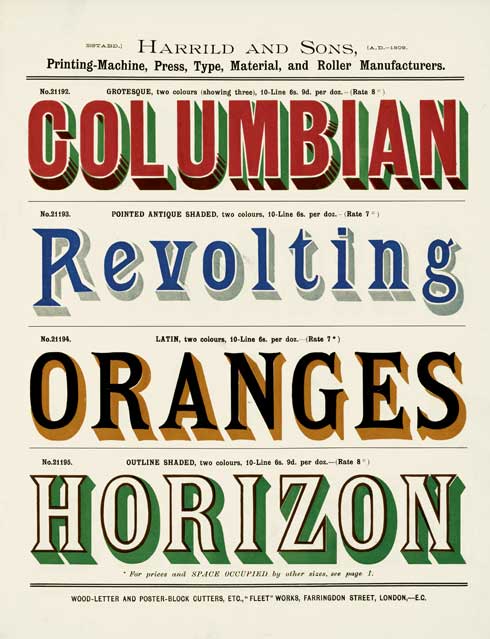
Ich staunte nicht schlecht, als ich eben von unserem Einkauf dieses Buch in die Hände gedrückt bekomme: Type. A Visual History of Typefaces & Graphic Styles, 1901-1938, herausgegeben von Cees de Jong im Verlag Taschen. Das Wunderbare bei diesem Werk ist der unbeschränkte Zugang zur Taschen-Online-Datenbank, auf der sich die Käufer des Buchs die 1400 Abbildungen als hochaufgelöste jpg-Dateien auf den eigenen Rechner laden können – zur freien Verwendung das oben gezeigte Beispiel hier herunterladen, 2 MB).
Das Buch bietet uns Schriftliebhabern einen kompetenten Überblick zum Schaffen der bedeutendsten Schriftentwerfer in den Jahren 1901 – 1938. Die auf einer angesehenen niederländischen Sammlung basierende Werkschau zeichnet die Entwicklung der Druckbuchstaben anhand ausnehmend schöner Schriftproben und -kataloge nach. Neben den Lettern sind auch Bordüren, Ornamente, Initialen und Verzierungen sowie exemplarische Lithografien, Schilder und Inschriften berücksichtigt.
Gezeigt werden Werke von William Caslon, Fritz Helmuth Ehmcke, Peter Behrens, Rudolf Koch, Eric Gill, Jan van Krimpen, Paul Renner, Jan Tschichold, A. M. Cassandre, Aldo Novarese, Adrian Frutiger und viele mehr. Die dem Buch beiliegende Taschen-Keycard ermöglicht den Zugang zur Online-Bilddatenbank: Über 1.400 hochauflösende Scans von Schriftmustern stehen zur unbeschränkten Verwendung bereit.